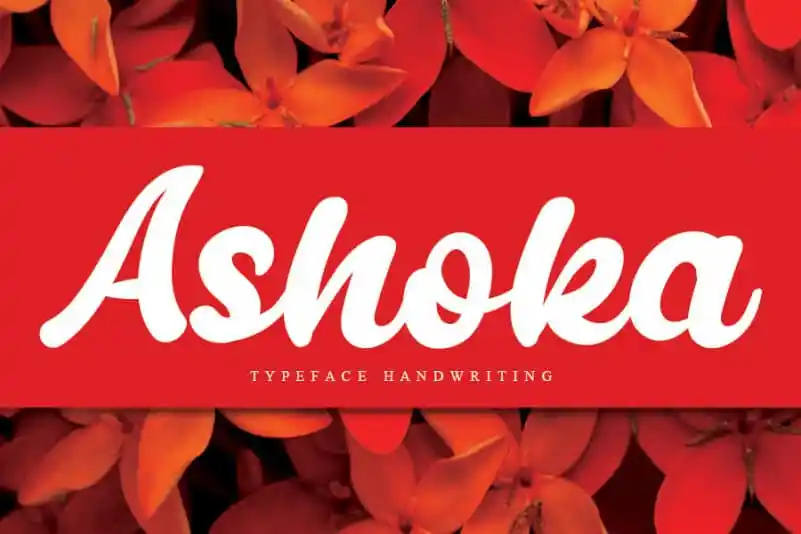
Ashoka Bold Script Font é uma elegante fonte escrita a mão com traços grossos e desenhados com um estilo ágil e grosso. Ideal para adicionar um toque único aos seus projetos gráficos, essa fonte poderosa fará sua marca se destacar entre as demais. Seja você designer de logotipos ou criação de materiais digitais em geral, Ashoka Bold Script Font é uma escolha perfeita para trazer seu trabalho à vida com personalidade e impacto. Adicione essa fonte poderosa ao seu portfólio de recursos gráficos e inspire seus projetos a crescerem. Designer: andikastudio